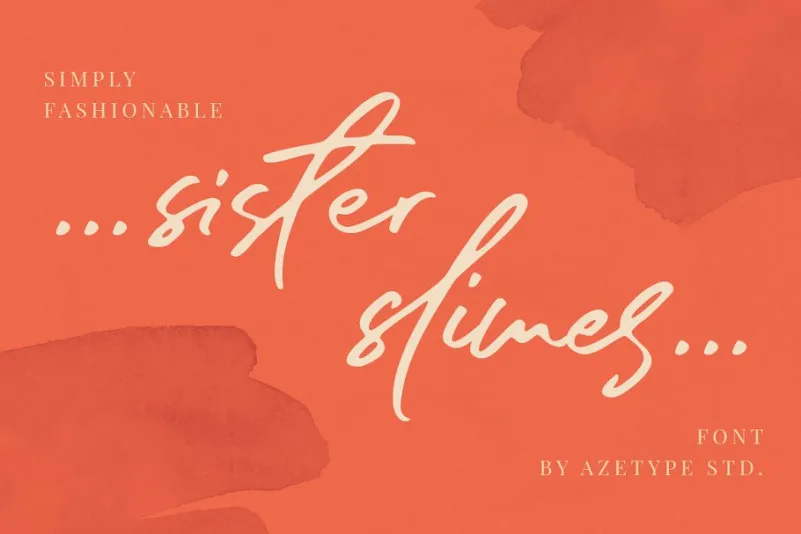
Sister Slimes Script Font – Download Grátis
Sister Slimes Script Font é uma elegante e moderna fonte a mão que enriquece qualquer projeto gráfico. Desenvolvida pelo designer Azetype Std., esta font traz um toque fresco e sofisticado aos seus designs, especialmente adequada para criações como cartazes de casamentos, logotipos pessoais ou de marca, material promocional, overlay nas fotos, publicações nas redes sociais, embalagens de produtos e muito mais. Com traços únicos que lembram as sujeiras das mãos humanas, ela adiciona um toque sofisticado e fashion às suas criações, tornando-a uma escolha ideal para aqueles buscando algo distintivo e atraente em seus projetos. Não perca essa oportunidade de enriquecer seu design com o charme inconfundível da Sister Slimes.